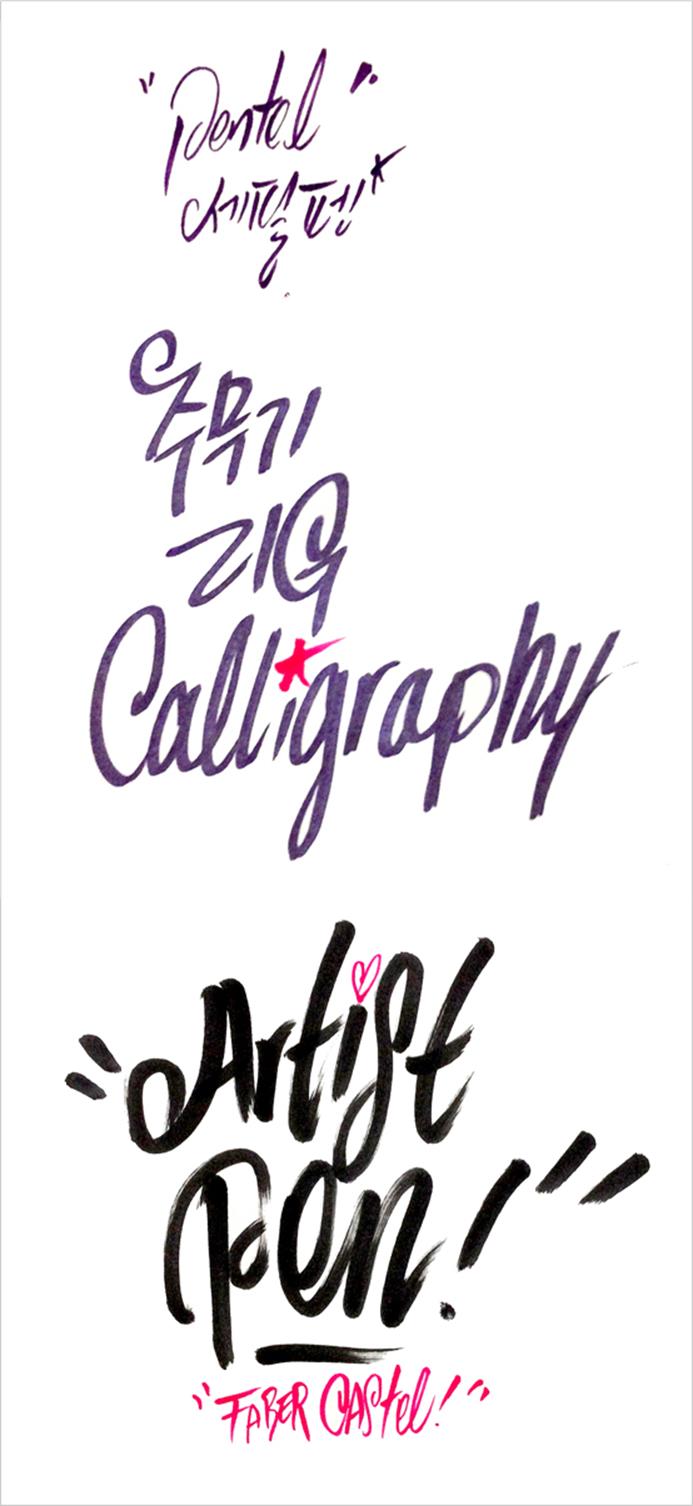
길 위에서 만난 손글씨, 장영호 캘리그라퍼
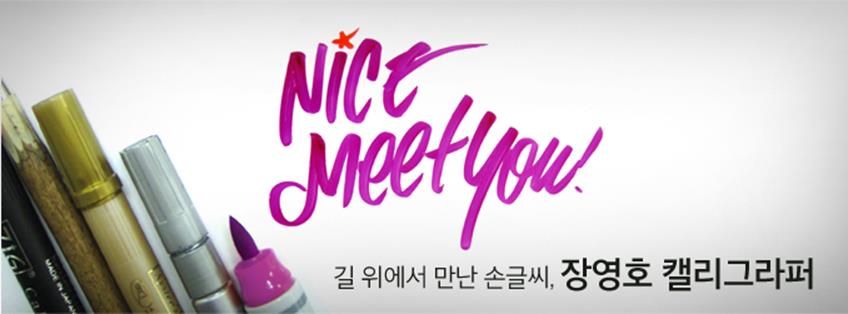
텅 비어있던 무지 노트가 바로 눈 앞에서 화려하게 변신한다. 고민고민 하다 적어달라고 뱉어놓긴 했지만 확신이 가지 않던 문구가 그의 손끝에서 가장 화려하고 설득력 있는 문장으로 돌변한다. 말 그대로 일필휘지, 화룡점정. 이 지경, 혹은 이 경지에 오르기까지 그는 얼마나 많은 연습을 했을까? 빈 공간만 보면 글씨를 쓰고 싶어 손이 근질거린다는 장영호 작가를 만나고 왔다.
안녕하세요. 장영호 작가님. 간단한 소개를 부탁 드릴게요.
안녕하세요. 저는 손글씨 쓰는 장영호라고 합니다. 꽤 오랜 기간 MF, MLB, EXR, POLHAM, 제일모직 등에서 VMD(Visual Merchandiser)로 일해왔는데요. 손글씨로 여러분들과 더 가까운 곳에서 호흡하고 싶어 거리로 나왔습니다. 노트에 손글씨를 써드리면서 여러분의 메시지를 전달하고 행복을 전해드리는 프로젝트를 진행하고 있는데요. 주로 강남역 근처 카페 거리와 신사동 가로수길에서 작업하고 있습니다.
손글씨와의 인연은 어떻게 시작되었나요?
캘리그라피 작가들을 보면 서예, 붓글씨를 기본으로 하셨던 분들이 많은데 저는 펜글씨로 시작했어요. 어릴 적 기억을 되살려보면 아버지께서 선물해 주신 알파벳 펜글씨 교본이 계기였던 것 같아요. 영어 시간에 저 혼자 필기체로 필기할 수 있을 정도로 글씨 연습을 열심히 했던 기억이 납니다. 교회와 대학교 편집부에서도 계속 손글씨를 연습했고 친구들에게도 손글씨를 써주면서 캘리그라피에 대한 관심을 계속 이어왔죠.
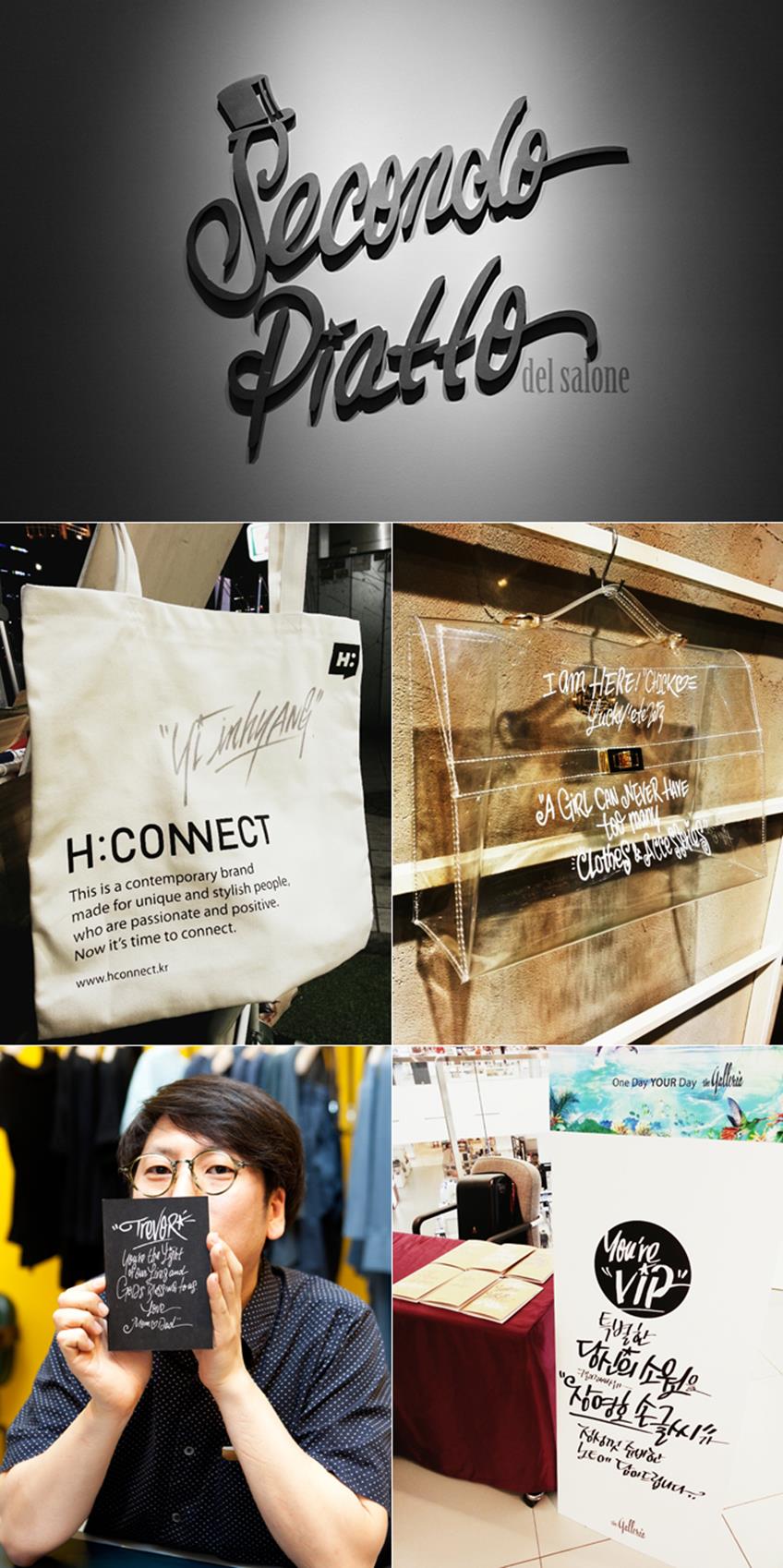
장영호 작가는 다양한 브랜드의 런칭 행사에 참여해 캘리그라피 이벤트를 진행하고 있으며 다수의 브랜드 로고 작업도 진행하고 있다.
손글씨나 서예를 공부하신 건가요?
제 전공은 의상디자인이에요. 산업디자인을 전공하고 싶었는데 이런저런 이유로 의상디자인을 전공하게 되었죠. 좌절하면서 재수를 할까 고민하고 있던 차에 서점에 가서 패션과 관련된 직업에는 어떤 것들이 있는지 살펴볼 기회가 있었는데, 그때 ‘패션 사진가’라는 분야를 알게 되었죠. 필름카메라를 초등학교 때부터 들고 다녔기 때문에 저도 패션 사진가라면 재미있게 일할 수 있겠다는 느낌이 들었어요. 그때부터 사진기 들고 컬렉션에 찾아 다녔죠. 수업보다 브랜드 모니터링을 했는데 학교보다 패션쇼에 가는 일이 더 많았어요. (웃음) 패션 브랜드 홍보담당자를 비롯해 패션 디자이너와 사진 기자분들이 참 많이 예뻐해 주셨죠. 그때도 ‘파워블로거’라는 개념이 있었다면 제 인생은 또 달라졌을 거에요. 정말 열심히 했거든요.
필름카메라를 어릴 때부터 들고 다니셨다고요?
네. 니콘(Nikon) 카메라의 전신이라고 할 수 있는 니코매트(Nikomat)를 사용했어요. 아직 갖고 있는데 초등학교 5학년 때부터 들고 다니면서 필름으로 사진을 찍었어요. 한 손에는 보온 밥통, 다른 손에는 카메라를 들고 다녔죠. 친구들을 찍어주고 인화해 선물해주면서 사진에 재미를 붙였어요. 그렇게 자연스럽게 사진을 찍다가 대학에 가서는 흑백사진연구회에 들어가 동아리 활동도 했죠. 필름 위에 제 손글씨를 쓰고 인화해 선물해주면 친구들이 굉장히 좋아했던 기억이 나네요.
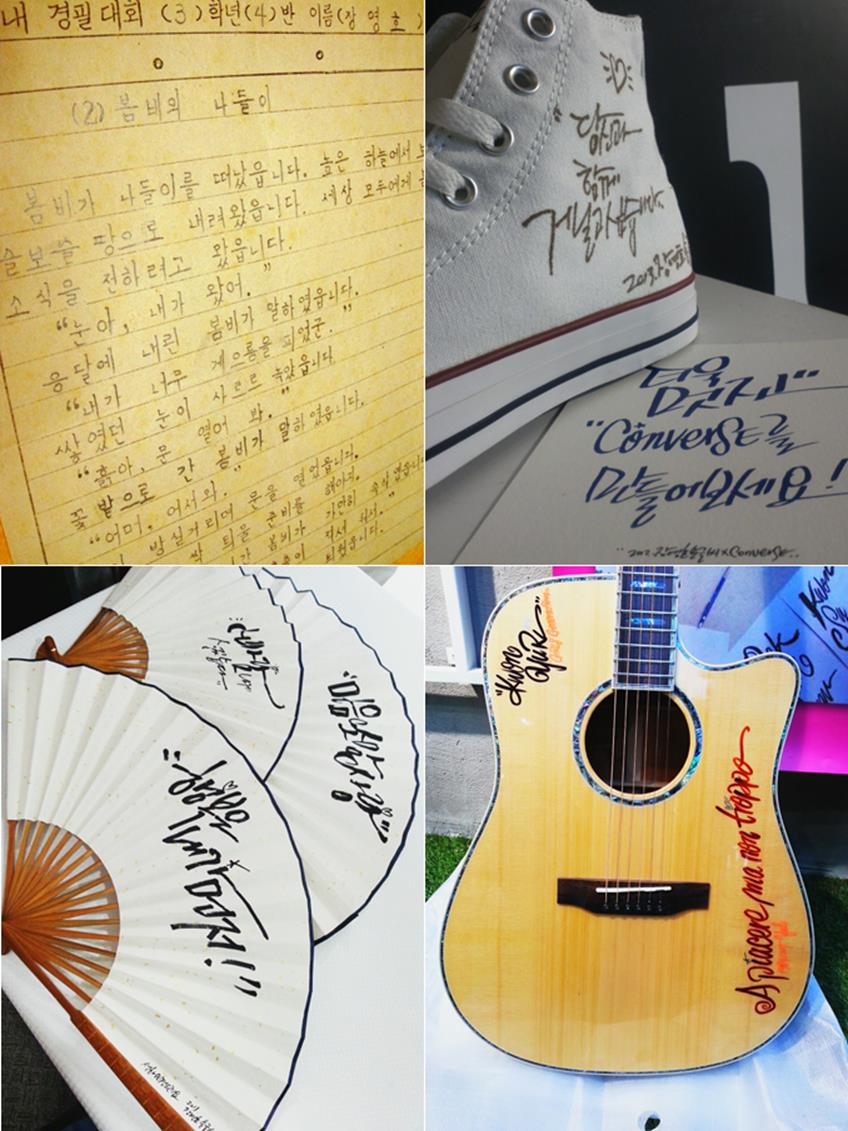
경필대회에 참가했던 어릴 적 장영호 작가의 손글씨와 다양한 물건 위에 써준 손글씨.
손글씨 노트 프로젝트는 어떻게 시작되었나요?
이렇게 거리로 나와 독립하기 전 3~4개월간 본의 아니게 두 가지 일을 병행했어요. 주중엔 VMD로, 주말에는 거리로 나와 노트에 손글씨를 써드렸죠. 그런데 아무래도 제가 더 좋아하는 일에 시간과 관심이 쏠리게 되더군요. 회사에서는 저를 믿고 일을 맡겨주셨는데 죄송한 마음도 들고, 일하기로 했던 계약기간도 끝나가는 시점에 노트와 필기구를 챙겨 들고 거리로 나와 팝업식으로 프로젝트를 진행하기 시작했어요. 페이스북(www.facebook.com/zhangyoungho)을 통해 입소문도 나고 다행히 많이 좋아해주셔서 즐겁게 작업하고 있습니다. 장마기간이 예상보다 길어져서 조금 아쉽긴 해요. (웃음)
길 위에서 프로젝트를 진행하시는 이유가 있나요?
바로 그 자리에서 예상치 못하는 여러 사람들과 교감할 수 있다는 점이 매력적이에요. 처음엔 작더라도 공간을 빌려 프로젝트를 시작할까 고민도 했는데 그 안에 들어가 있으면 지금처럼 더 다양한 사람들을 만나지 못하겠다는 생각도 들어요. 길에 나와 있다 보니 사무실에서는 만나볼 수 없는 분들을 만나게 됩니다. 그런 만남이 다른 손글씨 작업으로 연결되기도 하고요. 노트를 받아 들고 좋아해주시고 누군가에게 선물해주려고 걸어가는 뒷모습을 보면 희열을 느껴요.
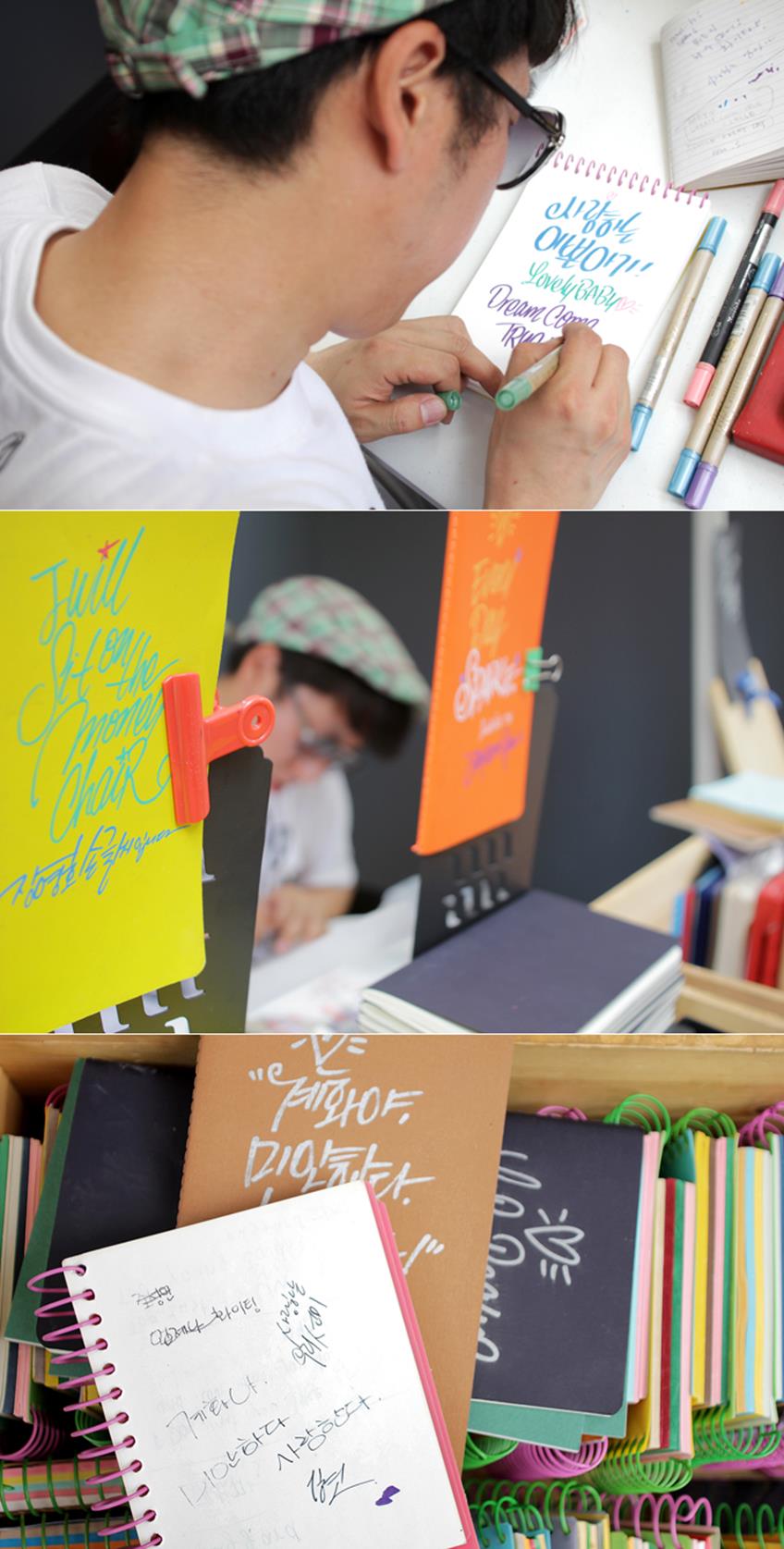
장영호 작가는 고객이 원하는 이름과 문구를 손글씨로 노트에 적어주는 프로젝트를 진행하고 있다.
반응이 굉장히 좋던데요. 이유가 뭘까요?
세상에 단 하나뿐인 노트잖아요. 초기엔 A4 같은 종이에 이름 석자만 써드릴 때도 있었어요. 그런데 생각해보니 그렇게 써준 종이는 쉽게 버려지거나 어딘가에 묻히게 되잖아요. 그런데 노트 표지에 손글씨를 써드리면 누군가에게 선물할 수도 있고, 노트를 쓰는 동안 손글씨를 계속 간직할 수 있죠. 그리고 예쁜 폰트들이 이미 많이 사용되고 있지만 그 폰트는 오직 ‘나’를 위한 글씨는 아니잖아요. 손글씨로 한 사람 한 사람 각자의 마음과 메시지를 그 자리에서 바로 써드릴 때 느껴지는 아날로그 감성이 가장 큰 매력인 것 같아요.
품질 좋은 노트도 한 몫 하는 것 같습니다.
손글씨 잘 쓸 수 있는 일곱 가지 팁
하나. S와 ㄹ을 공략하고 크게 쓰자
둘. 플러스팬을 눕혀서 써보자
셋. 형광팬에 검정 스탬프 잉크를 부어 써보자
넷. 손가락에 힘을 빼자
다섯. 비싼 팬 쓰지 말자
여섯. 복사지에 쓰지 말고 아트지에 쓰자
일곱. 글씨의 각을 맞추자
손에 힘을 주면 자유로운 워킹이 불가능합니다. 손글씨에서는 가장 기본입니다. 그리고 비싼 팬으로 쓰면 아까워서 연습할 때 마음껏 쓰지 못합니다. 아무래도 연습이 위축됩니다. 우선 저렴한 매직이나 플러스팬으로 마구 써보시고 비싼 팬은 나중에 선수가 되면 사용하셔도 됩니다. 그리고 복사지 말고 공연포스터나 전단 같은 종이에 쓰세요. 모조지 계열의 A4지는 종이흡수가 잘 됩니다. 그래서 잉크를 빨리 잡아먹죠. 아트지 계열의 전단지 등은 잉크 흡수가 더뎌서 팬과 종이 사이에 유막을 형성해 주기 때문에 마찰이 적습니다. 그만큼 휘리릭 빠르고 부드럽게 글씨를 쓸 수 있습니다. 물론, 글씨 성격에 따라 종이를 선택해 사용해야 하는 건 기본이겠죠.
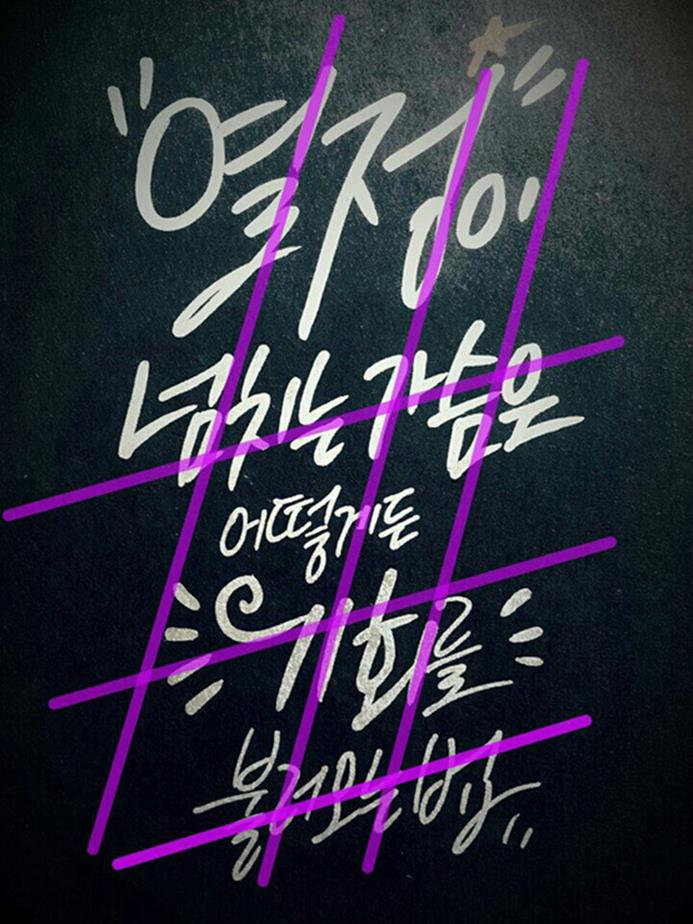
일정하게 각을 맞춘 보라색 선에 주목하세요. 이처럼 일정한 각을 정해 글씨를 써보면 조금 더 깔끔하게 정리된 글씨를 쓸 수 있습니다.
손글씨 작업할 때 신경 쓰는 부분이 있다면요?
일단, 망치지 말자. (웃음) 한 권에 몇 천원 하는 노트에 글씨를 쓰기 때문에 최대한 집중해서 글씨를 써야 해요. 고객이 써준 메시지를 어던 도구로 어떻게 쓸지 미리 머릿속으로 그려보고 이름은 틀리지 않았는지 확인하면서 신중하게 쓰는 것 외엔 크게 신경 쓰는 부분은 없어요. 기업에서 의뢰 받은 글씨도 거의 한 번에 써지는 경우가 많아요. 첫 번째 작업한 글씨가 대부분 가장 잘 쓴 글씨더라고요. 그래서 제가 노트에 손글씨를 써주는 작업이 가능한 것 같아요. 쓸수록 좋아지는 스타일이었다면 노트에 손글씨를 써주고 돈 벋는 일은 불가능했겠죠. (웃음)
주로 어떤 메시지를 적어 주시나요?
노트에 적어드리는 문구도 일부러 많이 준비하지 않아요. 메뉴판처럼 응원, 사랑, 남자친구에게, 여자친구에게 등등 주제별로 문구를 써놓으라고 말씀하시는 분들도 있는데, 고객들에게 조금이라도 생각할 수 있는 시간을 드리고 싶어요. 마음에서 우러나오는 글귀를 노트에 적어드리고 싶어서 시작했는데 글귀를 정해두면 다른 팬시노트와 다를 게 없잖아요. 노트 앞에서 뭐라고 써달라고 할지 우물쭈물 거리다 포기하고 돌아가는 분들도 적지 않아요. 그런데 젊은이라면 머릿속에, 가슴 속에 담아놓은 삶의 목표나 좋아하는 구절 하나 정도는 있어야 한다고 생각해요. 가슴 속에 품고 있는 고래 한 마리요. 저도 고객분들이 적어주는 글귀를 보면서 많이 배운답니다.
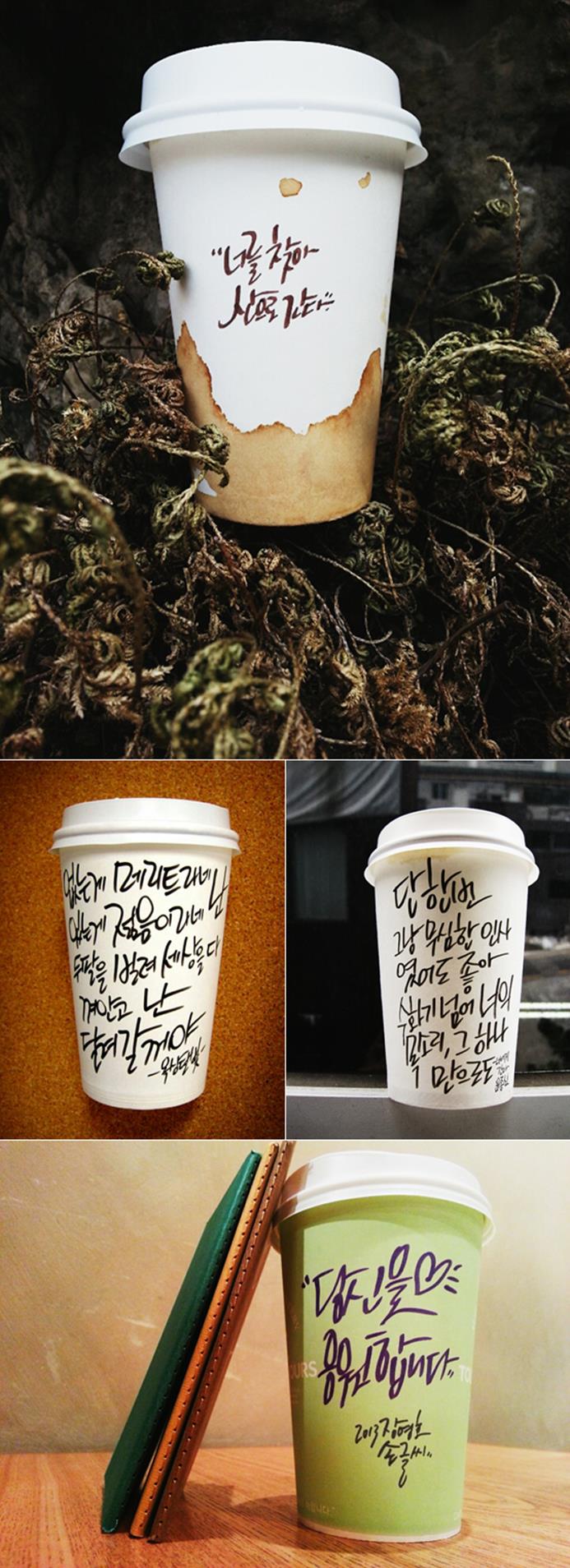
버려진 종이컵들이 장영호 작가의 손글씨와 만나 다시 태어난다.
‘컵 캘리’ 작업도 소개해주세요.
어느 날 회의를 하다 지루해져서 바닥에 나뒹구는 종이컵에 글씨를 써봤어요. 컵 캘리는 그렇게 시작된 작업이에요. 그냥 버려지기 아까운 것들이라 쓰레기통을 뒤져 그 위에 글씨를 쓰고 사진을 찍었죠. 그날그날 있었던 일을 쓰는데 벌써 1년이 넘었네요. 버리지 않고 모아두고 있는데 나중에 책으로도 정리해보고 싶어요.
좋아하는 작가가 있나요?
제가 정말 멋있다고 생각하는 작가는 아직 한 사람이에요. 영국 작가인데 유리를 가공해 글자를 만드는 분이죠. 전통 방식과 기술로 유리 위에 글자와 문양을 새겨 간판이나 장식물을 만드는데 그 과정을 보면서 감동 받았어요. 한번씩 아래 영상을 감상해보세요. 작품뿐만 아니라 작업 과정도 정말 예술입니다.
David A Smith – Sign Artist
로고 작업에 대한 소개도 해주세요.
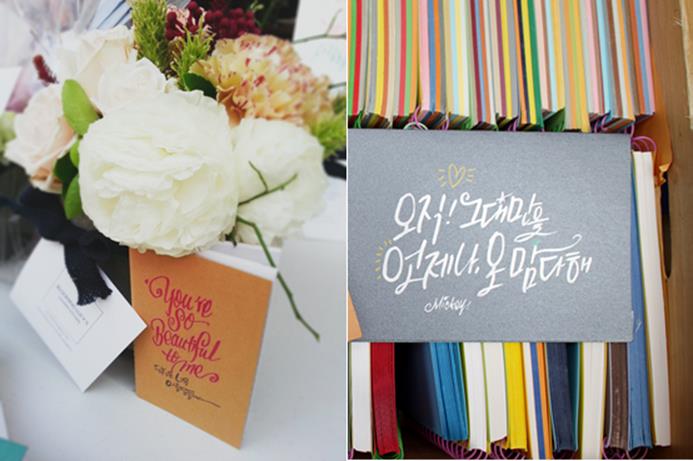
계획이 있다면요?
지금은 <장영호 손글씨 프로젝트 VOL.1>이에요. 이렇게 거리에서 언제까지 작업할 수 있을지 고민하면서 다른 프로젝트를 생각해보고 있어요. 노트는 비나 눈에 젖으면 상품 가치가 떨어지기 때문에 날씨에 영향을 많이 받거든요. 선물을 포장할 때 함께 동봉하는 카드를 손글씨 노트로 대체해도 좋을 것 같아요. 카드는 쉽게 버려지거나 잃어버릴 수 있지만 손글씨 노트는 선물하는 사람의 마음도 전달할 수 있고 오래 곁에 두고 사용할 수 있잖아요. 기회가 되면 책 작업도 해보고 싶어요. 우선 두 권 정도 구상하고 있는데, 하나는 이렇게 거리에서 손글씨 프로젝트를 하면서 모아둔 여러분들의 사연과 글귀를 정리하는 것이고, 다른 하나는 앞서 얘기한 ‘컵 캘리’ 작업을 정리하는 거에요. 그 전에 노트도 많이 팔고 행사에도 많이 참여하면서 최대한 캘리그라피와 손글씨 매력을 많이 많이 알리고 싶습니다. 강남으로 놀러오세요. (웃음)